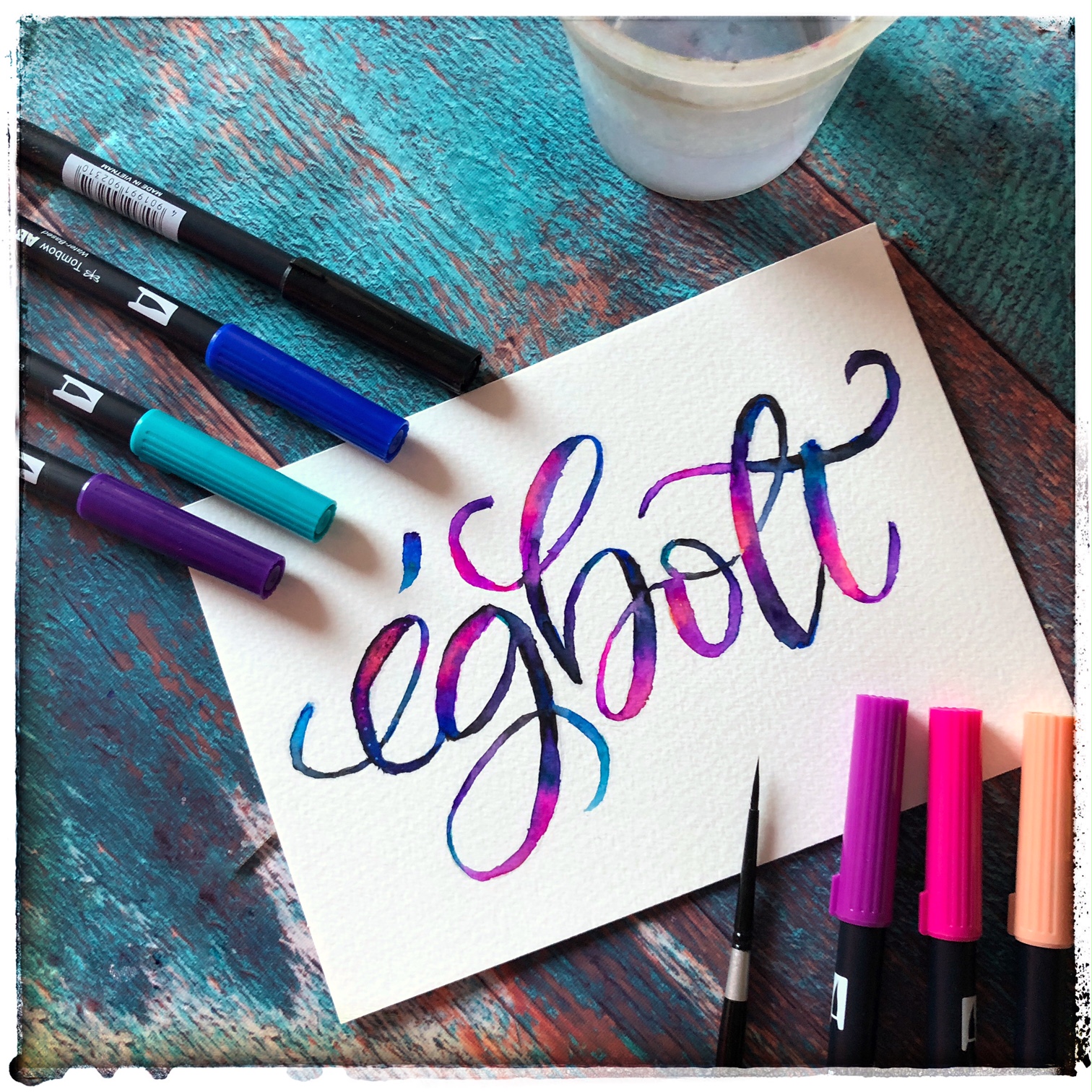
Bevallom nagyon tetszenek a galaxis hatással készült feliratok, illusztrációk, és talán az egyik legegyszerűbb hatás, amit el tudsz érni. Nézzük is meg, hogy hogyan kell elkészíteni.
Galaxis hatás ecsetfilccel
Az égbolt szót választottam példaként, amelyen bemutatom, hogyan érd el ezt a hatást.
A hagyományos, ecsetfilces verzióhoz először is egy kicsit vastagabb papírt ajánlok, hiszen az elért hatást vizes összemosással fogjuk elérni, így érdemes Mixed Media papírt választani, nekem a 200 grammos Canson a kedvencem.
Természetesen kellenek az ecsetfilcek, először is javaslok egy nagyon világos szürkét, ez lesz az alapunk ezt fogjuk kidíszíteni. Ezenfelül szükséged van még a galaxis színekre, ezek nem mások, mint a fekete, lila, többfélekék, magenta és lazac szín. Ezeket meg tudod vásárolni külön-külön, azonban mutatja a módszer népszerűségét, hogy szettben is kapható.
Az összemosáshoz használhatsz vizet és egy sima ecsetet, vagy kapható blender is az ecsetfilcekhez.
Első lépésként ceruzával szoktam felskiccelni a szöveget, ezt gyurmaradírral halványítom el, majd jöhet is a halvány szürke. Most modern kalligráfiát választottam, mert ez kellően vastag, hogy jól érvényesüljön a hatás.
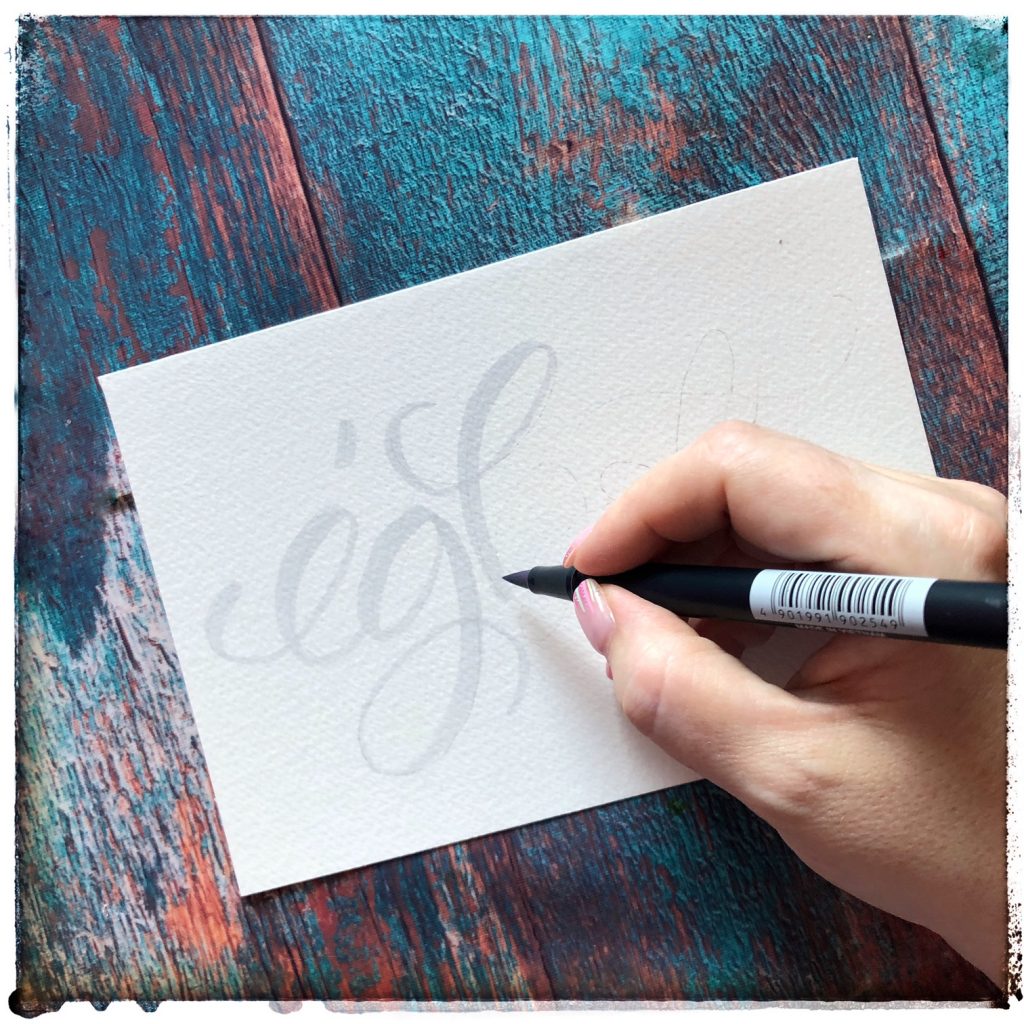
Ezután elkezdem a színezést, úgy, hogy foltokat rajzolok a betűk különböző részeire. belülre a világosakat, kívülre a sötétebbeket, végül a feketével körbe rajzolom.
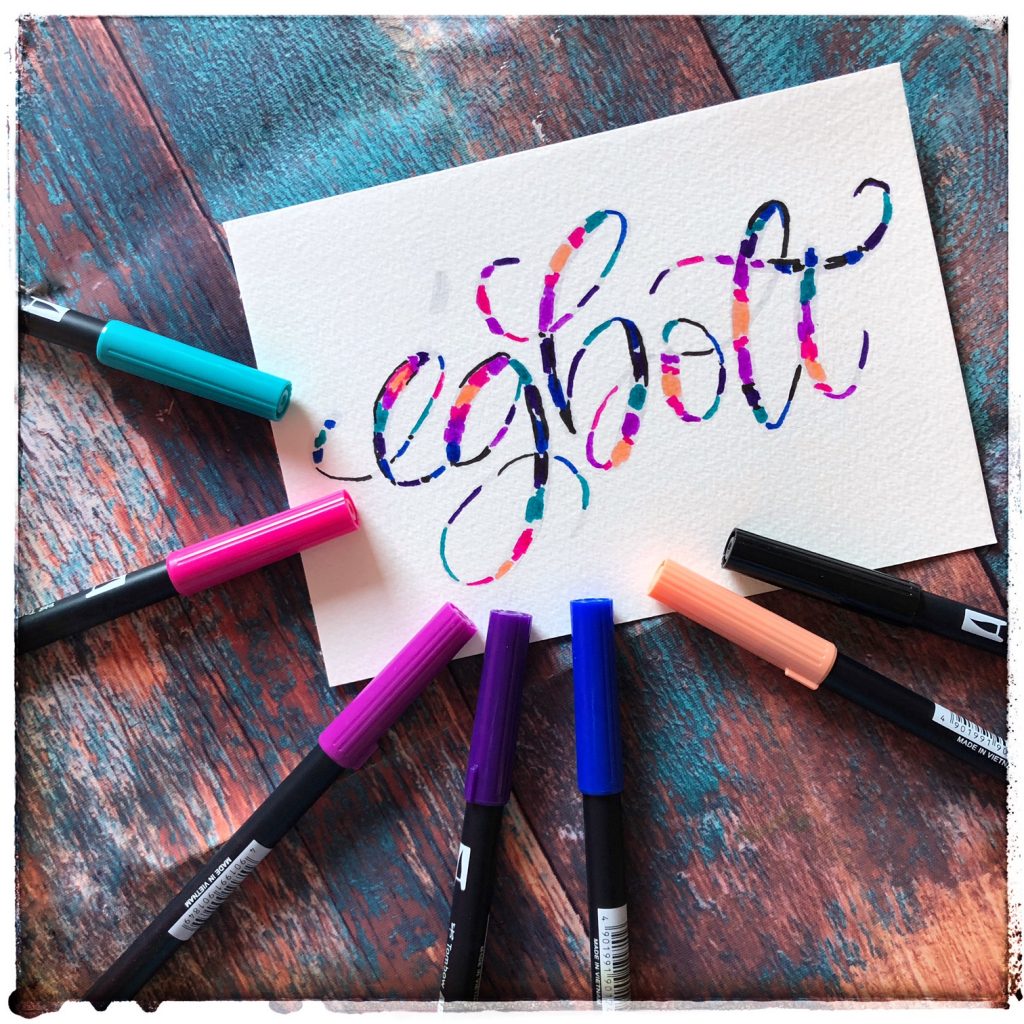
Most jöhet az összemosás. Erre használhatod a blender ecsetfilcet, javaslom, hogy belülről, a világosaktól kifelé kezd, mert különben, minden sötét lesz. A blender filcet érdemes néha kitisztítani, egy másik papíron húzz néhány ecsetvonást, mert különben minden csak fekete lesz. 😊 Blender helyett használhatsz egy sima ecsetet és vizet, bevallom ezt a módszert jobban szeretem, kevésbé veszi igénybe a papírt. Addig mosd össze a színeket, amíg el nem éred a neked tetsző összhatást.
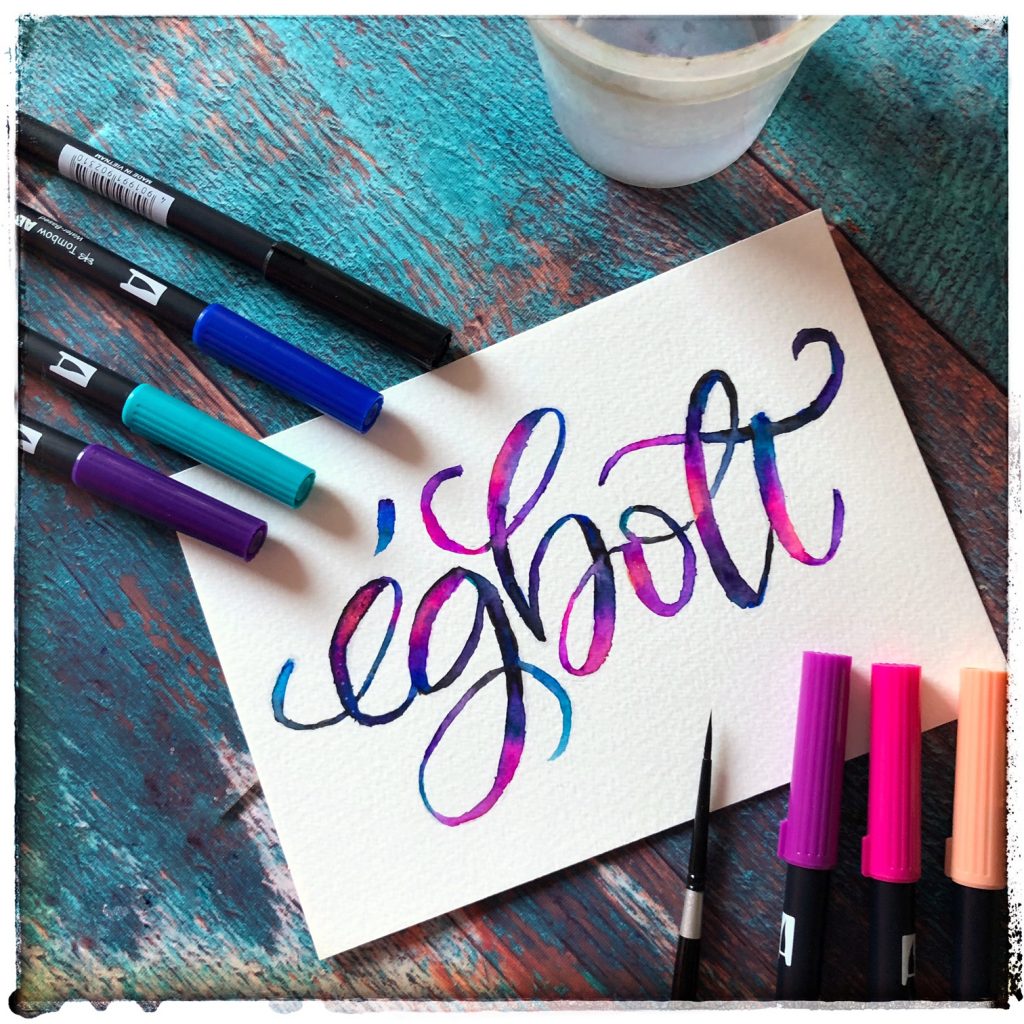
Galaxis hatás digitális módszerrel
Ehhez a Procreate programot fogom használni az iPademen az Apple pencillel. Előre is elnézést a sok angol szóért, de a program angol, így könnyebben fogsz eligazodni.
Először készítsük el a galaxis hátteret. Ehhez szükséged lesz akvarell hatású ecsetekre, brushokra egy wash típusúra, egy blend típusúra, illetve adhatsz hozzá még néhány akvarell stampet, hogy még élethűbb legyen a hatás, illetve egy akvarell papír háttérre. Ezek a brushok, papírok általában ingyenes formában is elérhetőek (Google a barátunk, íme egy példa ), így nem kell külön költened rá. Nyiss egy új layert és innen ugyanazt a módszert tudod követni, mint az ecsetfilceknél. Tehát először középre a világos színeket, majd a sötétebbeket, itt egymásra festhetsz nyugodtan. Végül feketével a keretet rajzolod meg. Aztán a blenddel tudod még szebben összemosni a színeket, illetve a stampekkel még élethűbbé tenni. Ha elkészültél, kapcsold ki ezt a layert.
Jöhet egy következő layer, amit ez alá tegyél be. Válassz bármilyen kalligrafikus ecsetet, sőt egyébként vannak akvarell lettering ecsetek is, és válaszd ki a fehér színt, írd le ezzel a kívánt szöveget, szót. Én maradtam az égbolt szónál. És innen már csak egy lépés, válaszd ki azt a layert, amin a galaxis háttér van, koppints rá és a jobb oldali listából válaszd a clipping maskot és tedd láthatóvá, és már készen is vagy!
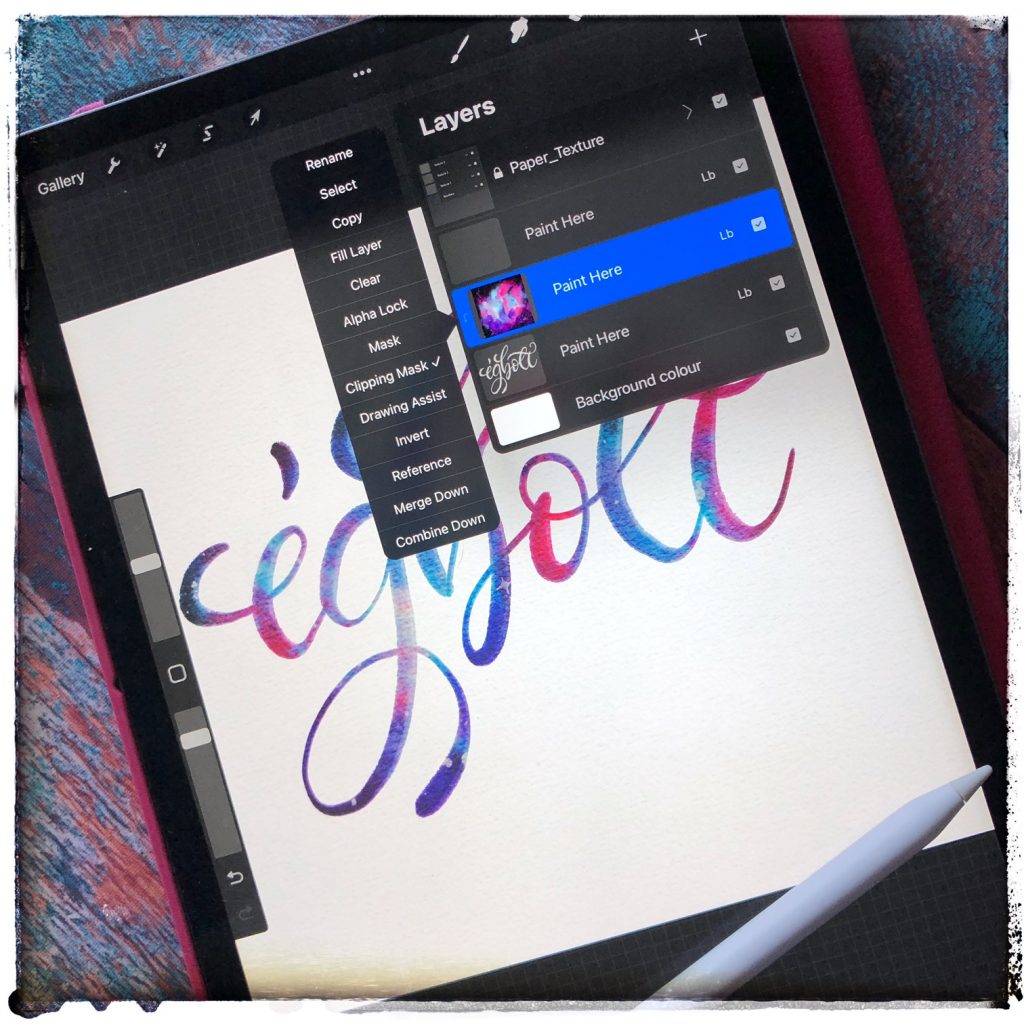
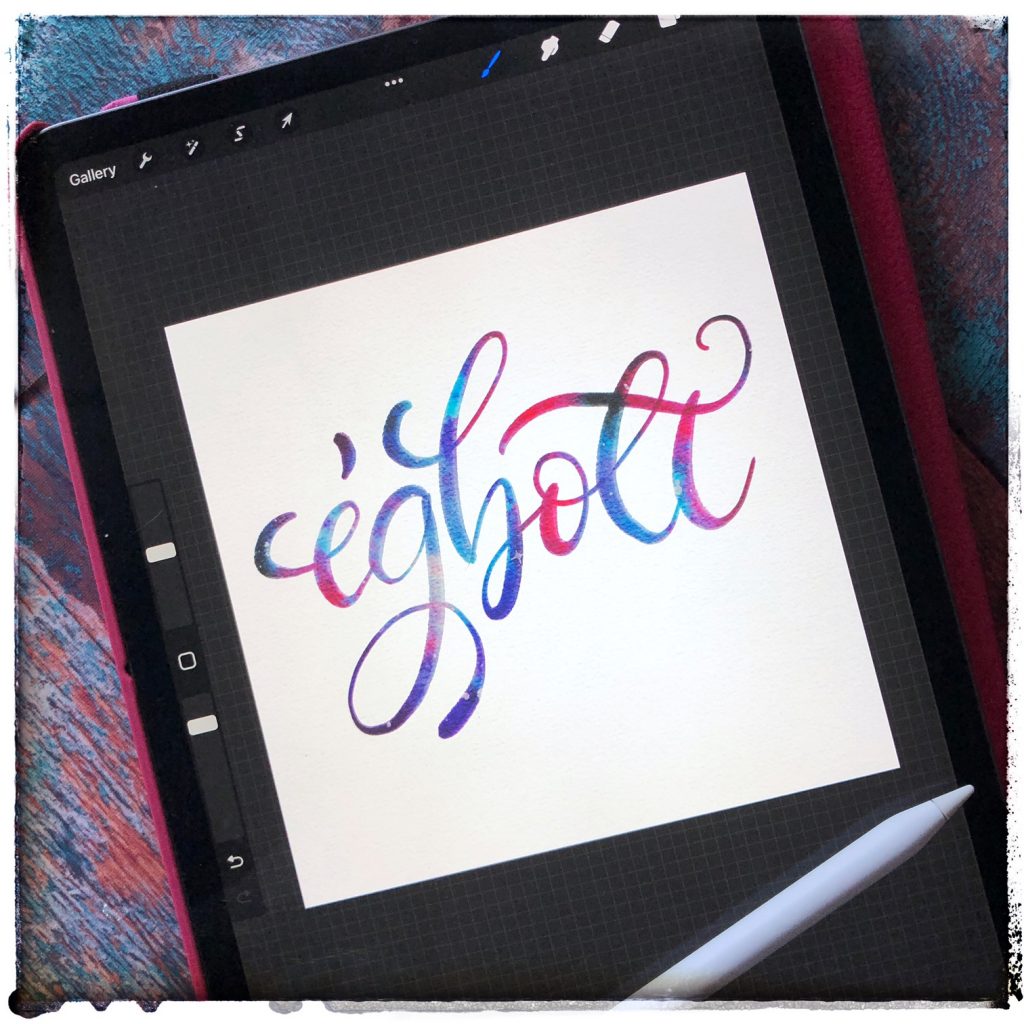
Plusz 1 tipp
Ha csak egyszerűen egy galaxis hátteret szeretnél, akkor fogj egy zacskót, vágd szét, színezd be a különböző galaxis színekkel, spricceld le egy kis vízzel.
Majd nyomj rá egy papírt, voilá készen is van a háttér. Várd meg, hogy megszáradjon és már írhatsz vagy rajzolhatsz rá!